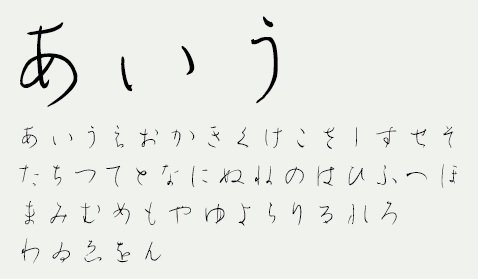
高野切のうち、もっとも現代風であると評される第三種の書風で
フォントを作成しました(ひらがなのみのフォントです)
ウェイト見本
- NSK高野切第三種フォント/w1
- NSK高野切第三種フォント/w2
- NSK高野切第三種フォント/w3
- NSK高野切第三種フォント/w4
- NSK高野切第三種フォント/w5